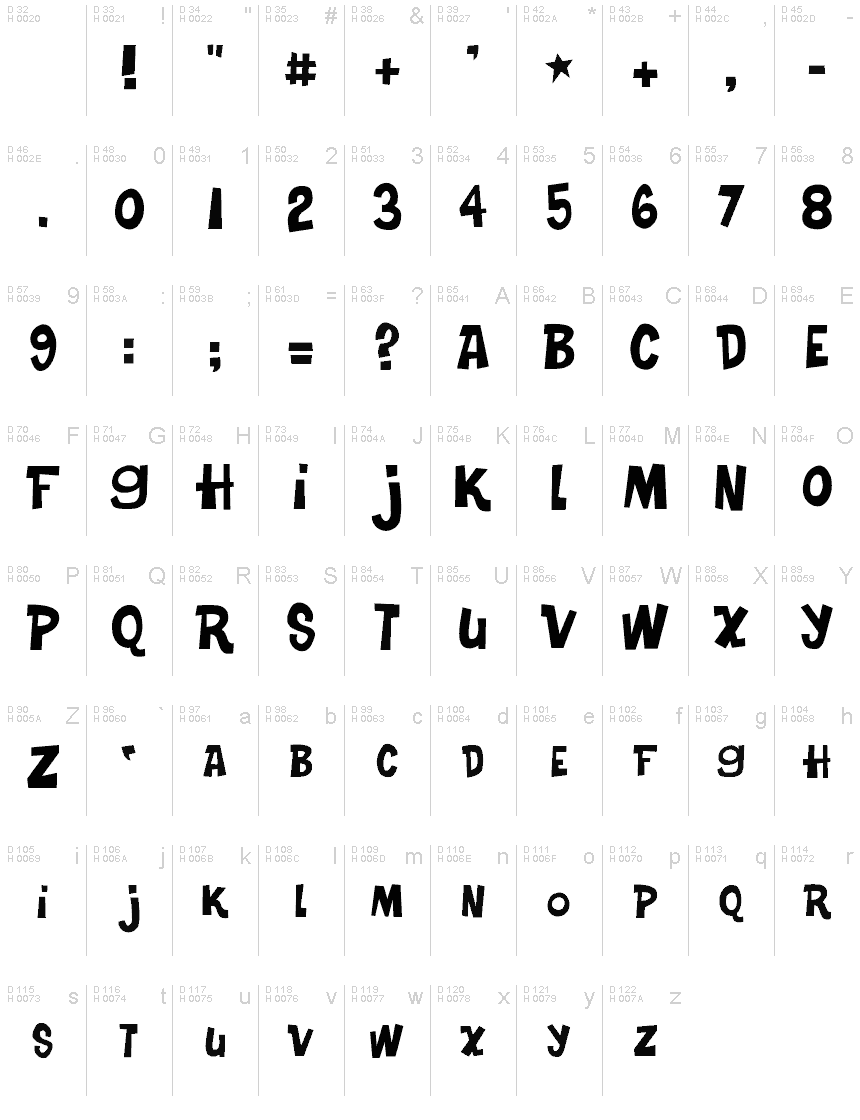
Turkey Sandwich, созданный Джоном Мартцем, — это яркий акцидентный шрифт в очаровательном мультяшном стиле, который мгновенно придает характер и живость любому проекту. Его массивные, игривые буквы излучают веселье и креативность, что делает этот шрифт идеальным выбором для проектов, ориентированных на молодую аудиторию, или брендов, стремящихся добавить в свою идентичность нотку юмора и непринужденности.
Благодаря своей плотности шрифт отлично читается, что позволяет гибко использовать его в самых разных творческих задачах — от броских заголовков до анимированной графики. Turkey Sandwich обладает эстетическим обаянием, способным подчеркнуть визуальную историю в детских книгах, динамичных рекламных кампаниях или интерфейсах казуальных игр.